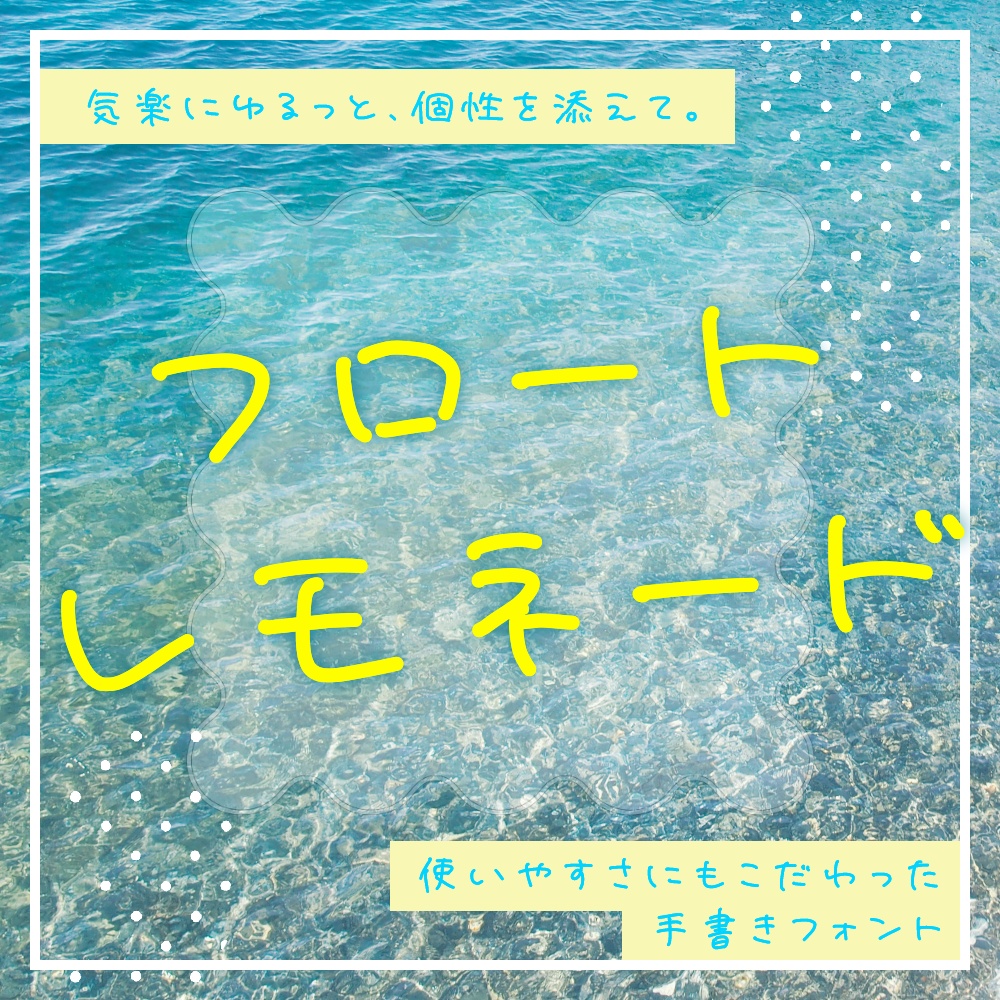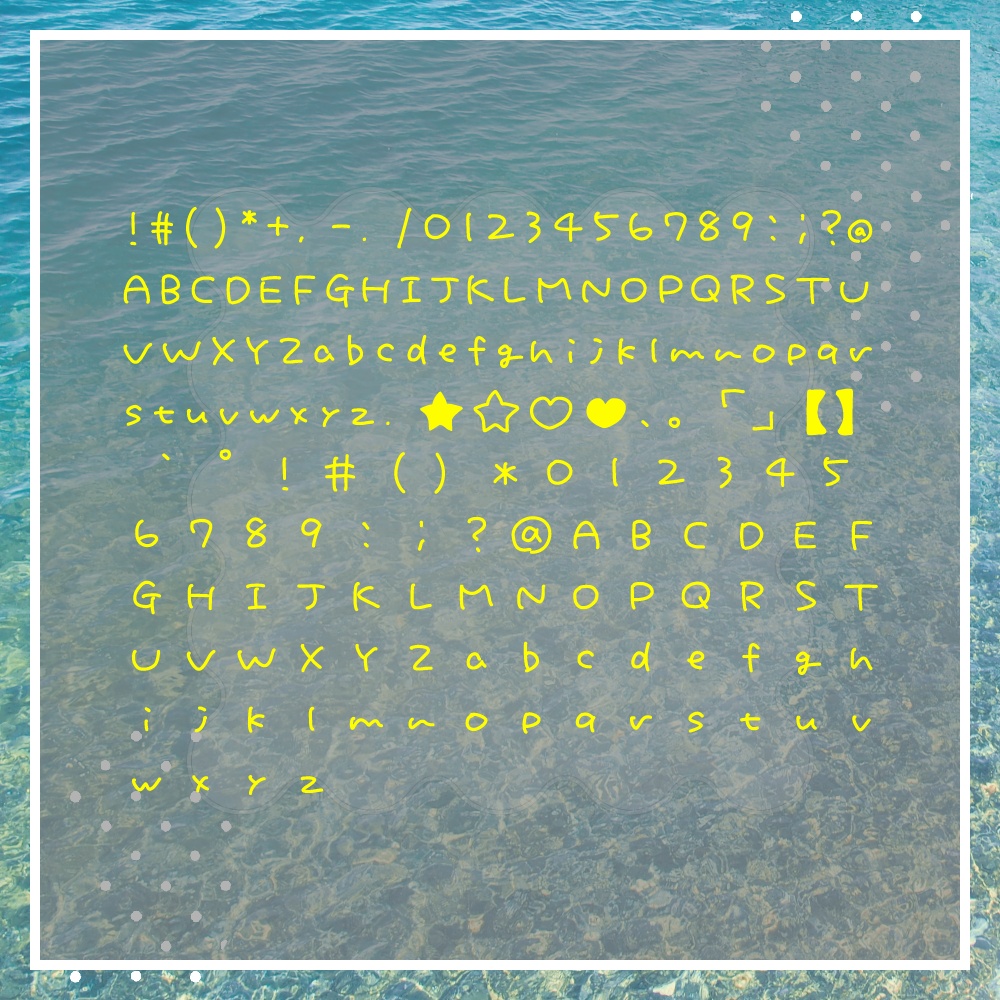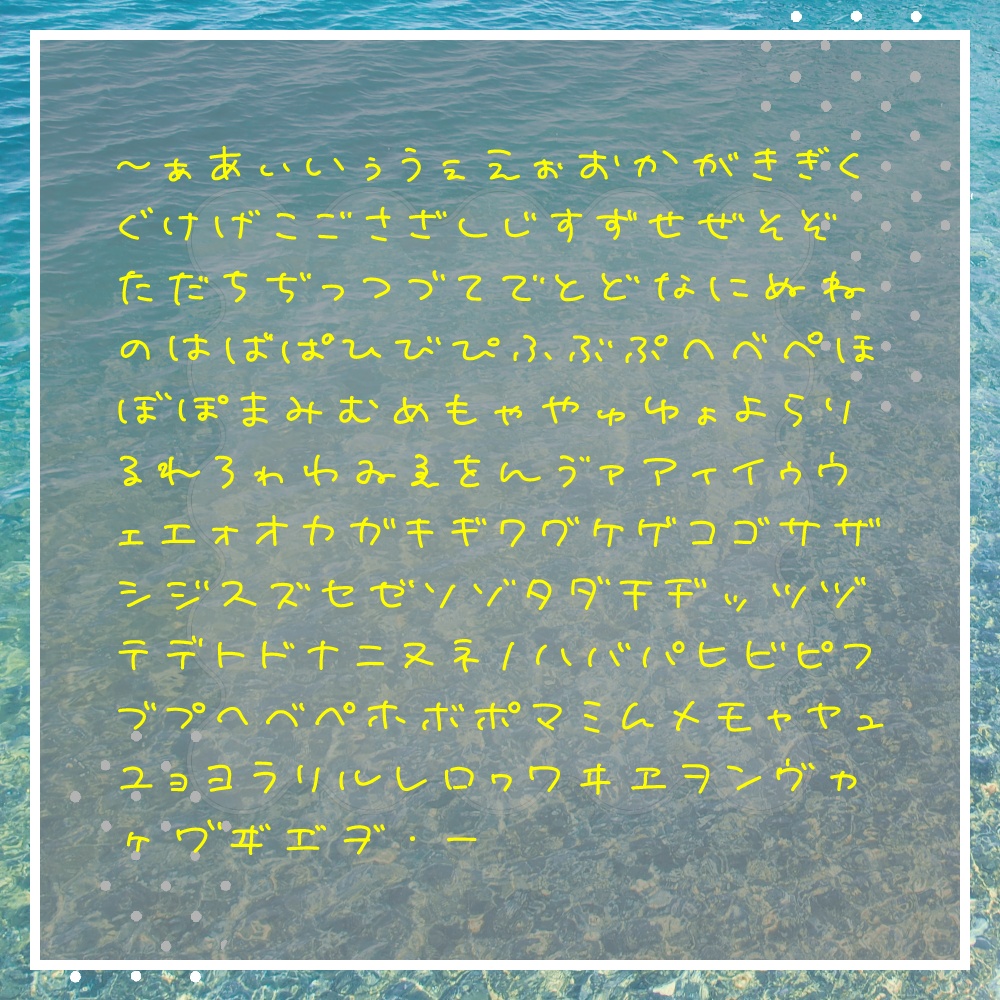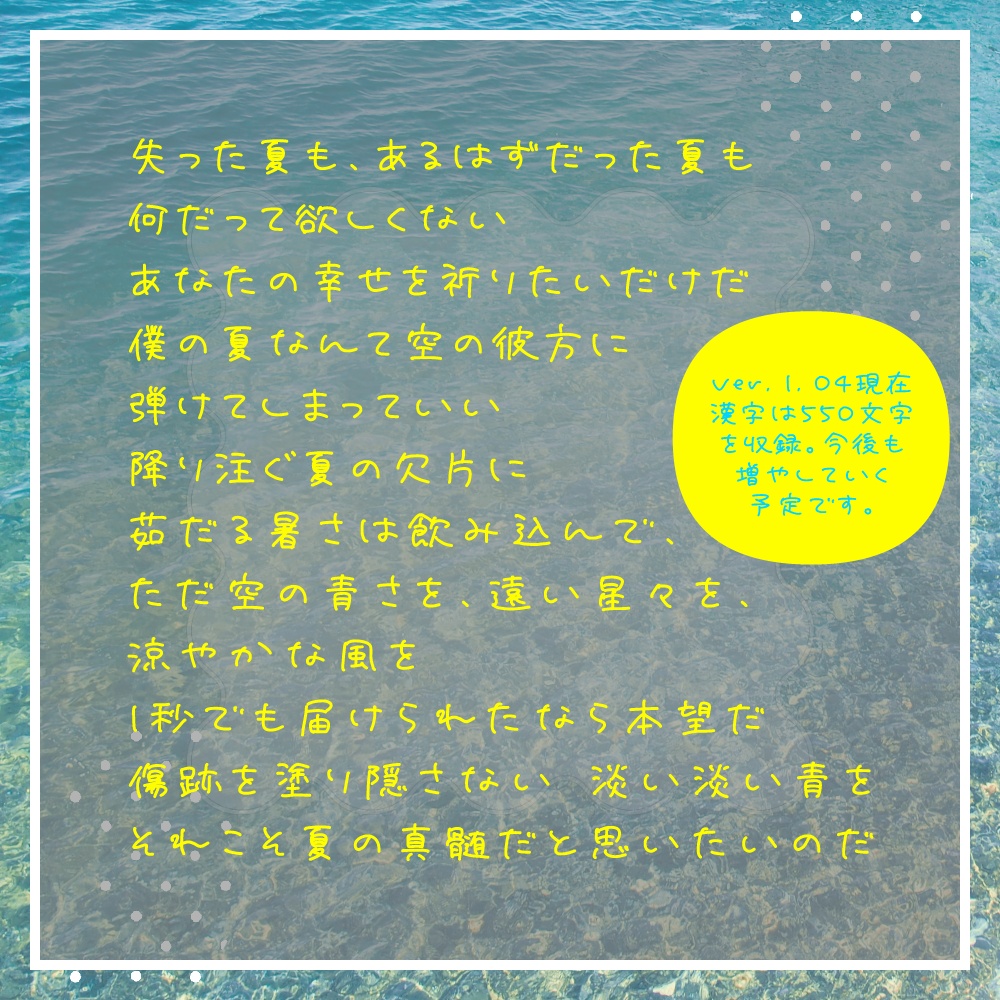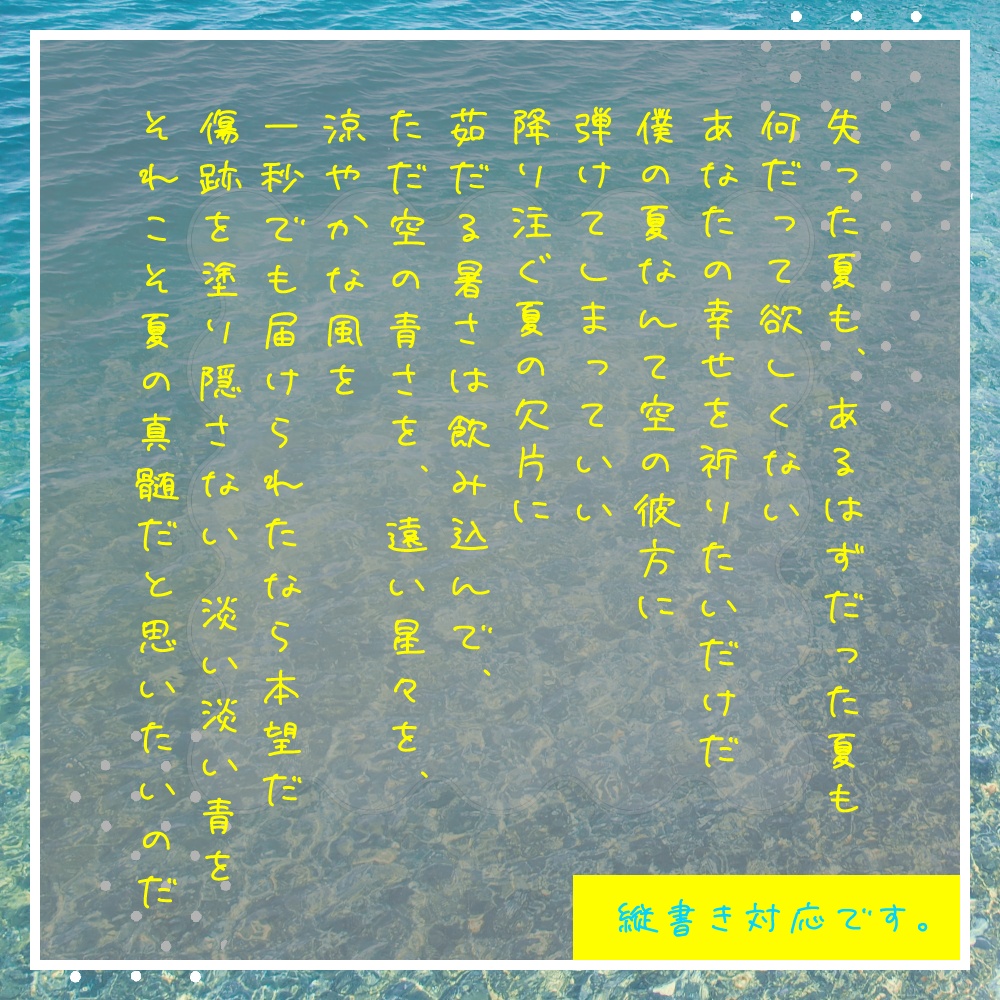
【フリーフォント版】フロートレモネード1.06
こちらのフリー版は【 商用利用禁止 】です。 商用でのご使用には商用版ライセンスをご購入ください。 DL前に必ず下記URL先より利用規約のご確認をお願いいたします。 https://berrymilksugar.com/font/ ---------------- * 26.09.27 ver.1.06にアップデートしました。 漢字を追加しました。 ---------------- 気楽にゆるっと、個性を添えて。 使いやすさにもこだわった手書きフォント。 クセがありつつもナチュラルで、使いやすい書体を目指しました。 気ばらないけれど、エモかわの味を乗せたいときなどに。 手書き文字としてはやや太めに制作しているため、視認性のよさもポイント。 親しみやすさのなかに、すこしだけ特別な空気を添えてくれるフォントです。 今後も積極的に漢字追加のアップデートを行う予定です。 常用漢字を揃えることを目標としています。長い目で見守っていただけますと幸いです。 (サンプルではやたら難しい字が打てるように見えますが、打ちたい字を優先して実装しただけなので、現状打てる漢字はまだわずかです。) ・OpenType、TrueType形式 / プロポーショナルフォント / macOS 26.5.1、Windows11にて動作確認済み ・収録文字はひらがな、カタカナ、英数字、各種記号、一部の漢字(788文字) 合計 1132文字 ---------------- 【投げ銭版】(追加文字のリクエストを受け付けています。) https://berry-milk-sugar.booth.pm/items/8548241 【商用版】 https://berry-milk-sugar.booth.pm/items/8548248 もあります。 お気に召しましたら、なにとぞよろしくお願いいたします。 SNS等でのシェアもとても励みになります……!